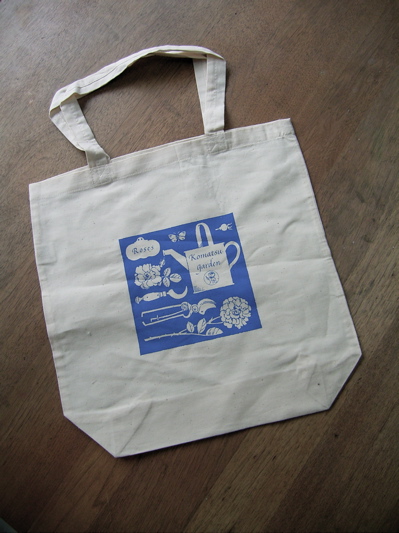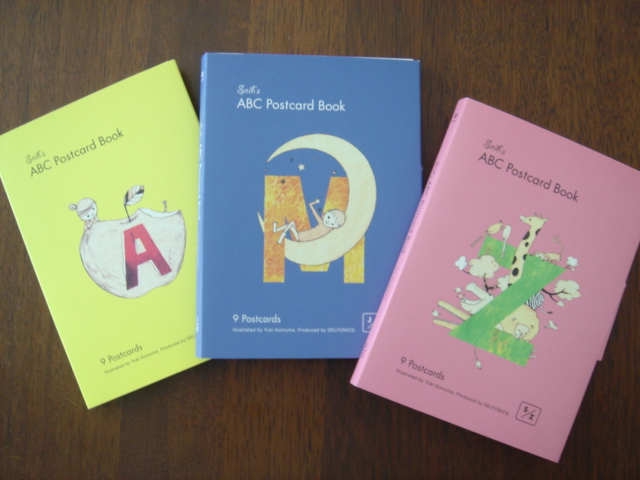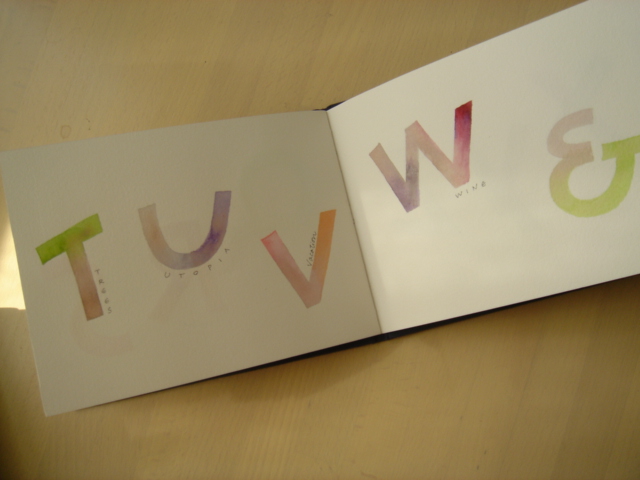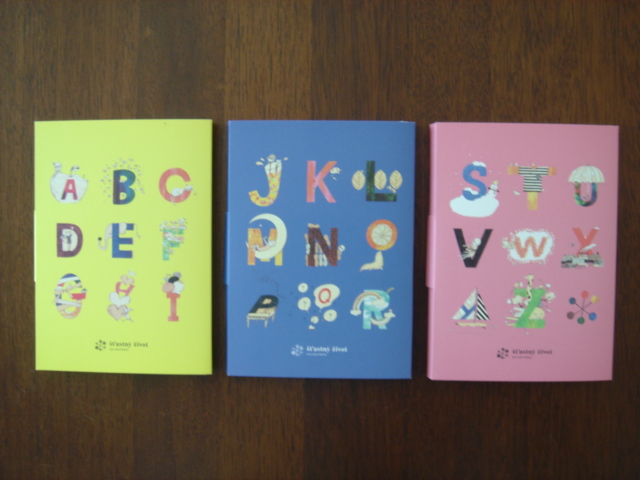
コンパスを使うとき
クラスのkaoruさんがExLibris(蔵書票)を制作しました。ビルトアップの最終の課題でした。インクとペンが入っていて、カリグラファーだということが一目でわかりますね!(ExLibrisは、この本の持ち主がどういう人かがわかるデザインが好ましいのです)
今回の形は円形で、ぐるりとラテン語のモットーが書いてあります。
Omne Pulchrum Amable
すべての美しきものは好まし。
コンパスで線を引いて切ったとおっしゃっていましたが、
あら? この円形、コンパスの穴がありません。
なぜなぜ!?
kaoruさんにとっても良い事を教えてもらいました。ある道具を使うのだそうです。
これです。
ほぉ〜〜〜!なんという優れもの!
教えてもらうまで、我が家にこんな物があるなんて気がつきませんでした。
これはうちの相方さんが学生の時に大学の授業で使うために買わされた製図道具です。大昔にもういらないからともらって、コンパスとディバイダーなどを使っていました。
kaoruさんに見せたら、これですよ、と教えてくれました。なるほどね〜。持っていはいるけど使い方を知らない道具って一杯あるんだろうなぁ・・とつくづく思いました。
これからは、穴空きにしたくない時にこれを活用しましょうね
皆さんの家にも、もしかしたらあるかもしれませんよ。特に理系の学生さんがいるorいたご家庭はね!
粋な手拭い
今や手拭い専門店もある今日
この頃。
軽くてコンパクトで…。
今回は、また面白いデザインを見つけました。そのタイトルも「NIPPON」とな。
シンプルな図案がいいですね。見ながら説明できたら話しも盛り上がることでしょう〜。
でもTEMPURAはツェッペリンに見えなくないかも?
こちらは「手影絵手本」とな。
ぁあ〜、懐かしい!
子供の頃は遊びましたねぇ〜。
おばあちゃんに教えてもらいました。幼稚園でもやったような…。
海外では、どんな手影絵があるのでしょうねぇ〜?
鳴き声の違いとかすると面白いかもしれませんね…。
太陽の光が透明で強い1月あたりが撮影には
良いかと…。
風と戦いながら〜。
もう少しで1月も終わりですね…。
恵方巻きの紹介も始まり…、食べなきゃ!
福永さんのエコバッグ
ご存知福永由美子さんデザインのエコバッグをゲットしました。彼女のイラストはもちろん、文字も入っていますぞ!
これは山梨にあるコマツガーデンさんのノベルティグッズで福永さんがデザインされました。
コマツガーデン
バッグにはちゃんとマチもついていて、軽いししっかりしていて、バッグの中に忍ばせておくのにピッタリです。
最近はエコバッグをちゃんと持ち歩いている人が本当に増えましたね。これは自分の好みに合ったセンスの良いエコバッグが手に入る様になったからかもしれませんね。ちょっとおしゃれ、というのが物やデザインにこだわる人たちには必要条件です。
これはノベルティグッズですが、今週末吉祥寺で開催されるArt 雑貨&Cafe展では、福永さんのオリジナルエコバッグが出品されるそうですよ!
15名の作家が参加しての、アート雑貨の展示&販売されます。
寒いんですよ〜、根性なしですみません。
風邪もはやっているようですね。モジトルメンバーも風邪にやられています。
あれ、元気なのは私だけかも?
毎回、冬は繰り返し風邪をひきガラガラ声の私ですが、1ヶ月後に歌の発表会を控え
今度ばかりは喉を荒らすわけにはいきません。風邪対策にも気合がはいっております。のど飴、常備品です。いろいろな種類が出ているので、試すのも楽しい、ついいろいろ買っちゃいます。
のど黒飴は効いている気がします。ミルク系も好き、というより効くのではないかというかすかな信頼。
高校時代、合唱団の先輩がコンクール直前に声が出なくなってしまったのですが、不二家の「ノースキャロライナ」というキャラメル(ぐるぐるうずまきの…なつかしい)を一袋なめ続けて、見事復活したのを見て以来、ミルク系は効く!と。
昔はのど飴というものが今のように売られていなくてせいぜい浅田飴か、スイス生まれのハーブキャンディー〜
くらいでした。ちょっと試してみたかった濡れマスク…自分で濡らしたマスクはすぐはずしてしまうんですけど、これはどうでしょうか?
私のイチ押しは「スカーフをのどに巻く」です。
使わなくなった小さめのスカーフをわりとキッチリ目に首に巻きます。寝るときはもちろん、見た目の差し支えがない限り巻いておきます。朝起きて喉がなんとなくざらつく、ということがこれでなくなりました。おばちゃんぽくてもスカーフ巻き!
緑茶でうがいするのもいいみたいですね。緑茶の殺菌パワーに期待できそう。
緑茶にお砂糖を入れて飲むというのを、声楽家になった先輩がやっていましたが、好みが分かれそう…紅茶ならおいしんですけどね。あとは、冷えないうちにさっさと寝る、に限るんですが、夜しか書けない日も多いので仕方ありません。
今年は寒いので暖かグッズ総動員です。子どもの頃からのお伴、タータンチェックの膝掛けとmojitor-hさんが譲ってくれた
電気のあったか椅子座布団です。(私が「寒い」を連発するので)
もちろん足元は羽毛入り室内履き。
みなさんはどんなふうにあったかくしてお過ごしなのでしょうか?
え?家は暖かいから薄着で過ごせるわ、って?うらやましい!
2008年01月25日
インゲさん!
ドイツのカリ人Ingeborg(インゲボルク)のことは、勝手にインゲと
呼んでます・・・。何も知らないインゲ・・・。ごめんなさい。
ずいぶん前に日本でWSをしてもらった時には、家族の話で
息子さんもずいぶん大きかったから・・・と月日は流れ・・・。
今年になって届いたグリーティングカードは何やら特別?
とてもセンスの良いかっこいい
レターとカード!
ふ〜む…何々?70回目の誕生日とな!ほほ〜だから今年は特別の
Neujahrskarte(新年のグリーティングカード)を作ったそうです!
なるへそ…確かにカードは七づくしの言葉が書いてありますよぉ〜。
SIEBENと読めるのが「7」です。
デザインも「7」ですね〜。
彼女が説明していた「Einladung」
(招待状)は、多分右?
グーテンベルグミュージアム脇の活版印刷工房で作ったとな!
ほほ〜Neulandの文字がかわいい!コントラストで綴られている
カーシブ文字の高さや…少し違うかもしれませんが、mojitor-sさんのやったグラデーションにも通じる部分がありそう〜。組み合わせの妙です!濃く見える部分と薄く見える部分のバランスが美しい〜!![]()
手紙の最後の部分に訳ありげに
書かれた言葉・・・ん?
「Dein ABC Klebeband ist wunderbar !」(ABCテープはイケテるわ!」
記憶を辿って・・・そうかそうか、
インゲに送った封筒にに貼り付けた
テープのことか〜。こまかいとこまで見とりますねぇ・・・。しゃーない、今度送ってあげよ〜。
・・・ということで、インゲに縁とゆかりがあって、mojitor-hの連絡先をご存知の方!
「古希を祝うインゲ」にお誕生日カードを出しますので、一緒に出しませんか?
2月10日までに、カードを我が家までお送りくださいませ!(事前にメールで送るとご連絡
頂ければ嬉しいです)
2008年01月24日
スキー四方山話
滞在した町は、St.Anton(サンクト・アントン)。チロル州とフォアアルベルグ州との境にあり、野沢温泉と姉妹都市です。
町の中心地はとても小さくて可愛いですが、背景にある山々は広大で、スキー場も
山々に分かれていて、7つほどの地域が
共通リフト券で滑れます。離れた地域を結
各宿が並んでいて、
部屋の空き情報は、看板に出ています!
便利です。
スキー場では、至る所に看板があり、各スキーヤーは自分の足と相談しながら滑ります。
ABCブック
むか〜し作ったABCブックです。
これを作ってみたいというご希望があったのですが、ちょっと迷っていました。
肝心の製本は私の力量ではこころもとないので…相談したら、製本がお得意のKyokoさんが指導を快く引き受けてくださることに。
よかった〜!材料の手配までお願いしてしまって大感謝、です。
これで、この春の自宅クラスのワークショップはABCブックで決まり!
私は水彩で色をつけていますが、中のレイアウトやサイズは各自で自由に考えてもらおうと思います。さあ、好きな言葉を見つけて、中身をがんばって作りますよ〜。
寒いけれど、机に向かわないと始まらない、ですねえ。
これを作ったときの私の言葉集めはMy favorite thingsでしたが、今度は何かテーマを持って作ってみようと思います。
こんなかわいいABCブックも、Kyokoさんの私物。(でしたよね?)
楽しいイラストのポストカードが9枚ずつ。使っていらっしゃるんでしょうか、やっぱりコレクション?
これも以前に作った手のひらサイズの本のサンプル…
しかし、未完成…
あー、こんなのばっかりが箱にゴロゴロしてます。反省、反省。